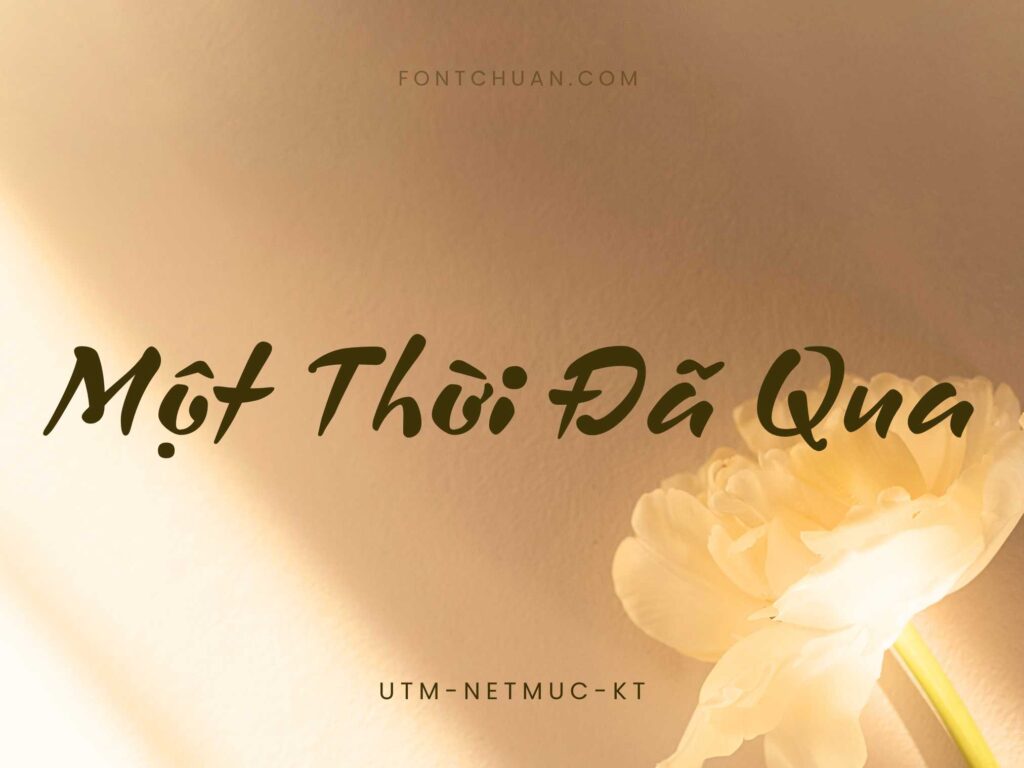
Font UTM Netmuc Kt Việt Hóa
Việt hóa bởi: Thiên Minh
UTM Netmuc KT là một font chữ trang trí nghệ thuật, đã được Việt hóa, chuẩn gõ tiếng Việt. Font này mang phong cách độc đáo, phù hợp cho các dự án thiết kế cần sự sáng tạo và khác biệt. Được sưu tầm và giới thiệu bởi thành viên của Font Chuẩn, font này đáp ứng nhu cầu của bạn đọc, cung cấp nguồn tham khảo chất lượng và ứng dụng thực tế vào các dự án thiết kế
Với thiết kế độc đáo và nghệ thuật, UTM Netmuc KT phù hợp cho các ứng dụng như tiêu đề, poster, biển hiệu và các ấn phẩm sáng tạo khác. Các ngành nghề như quảng cáo, ẩm thực, thiệp cưới và giáo dục có thể tận dụng font này để tạo điểm nhấn và thu hút sự chú ý trong các sản phẩm thiết kế
Tác giả: Justin Callaghan
Tác giả: Joanne Hewitt